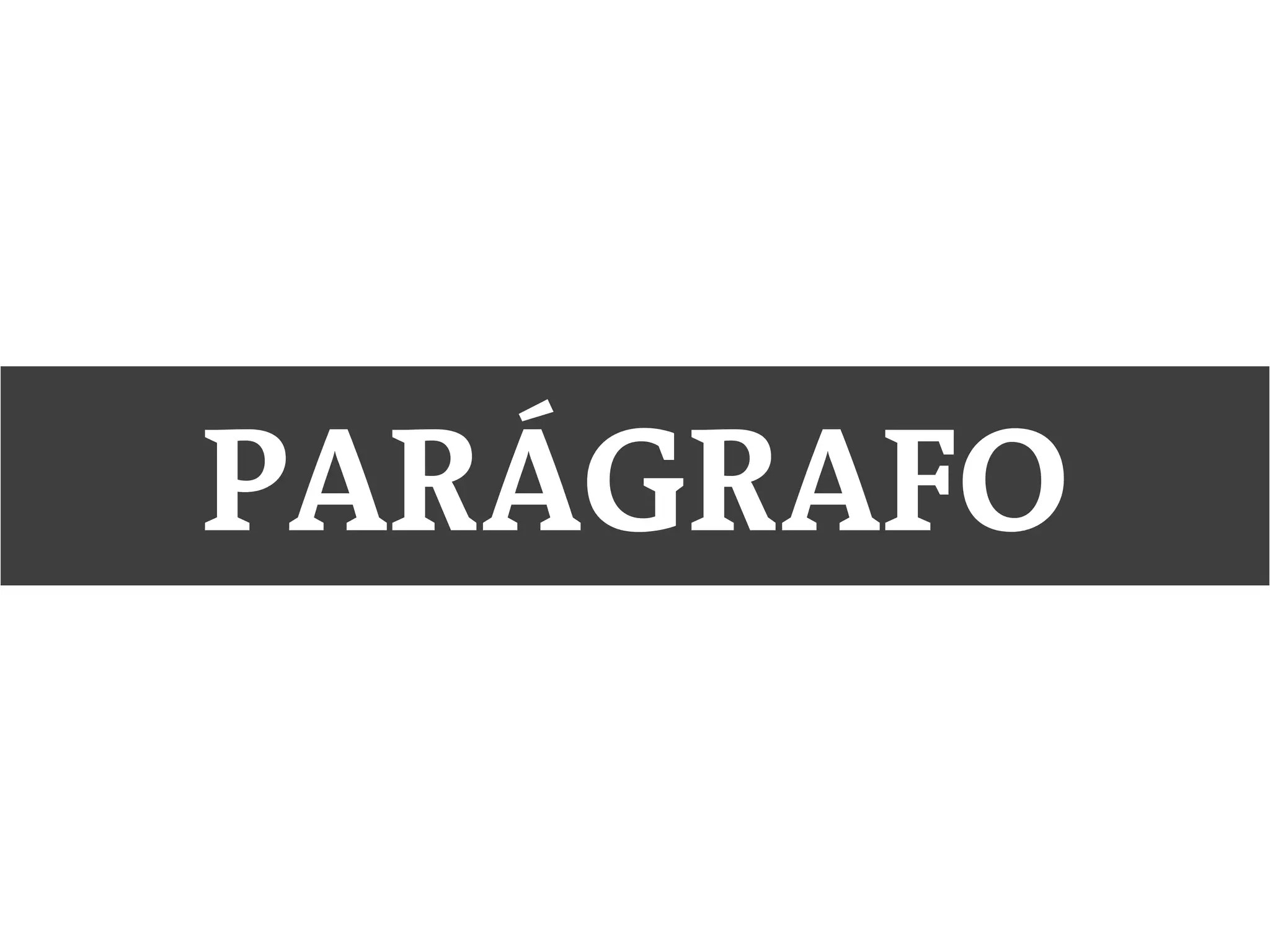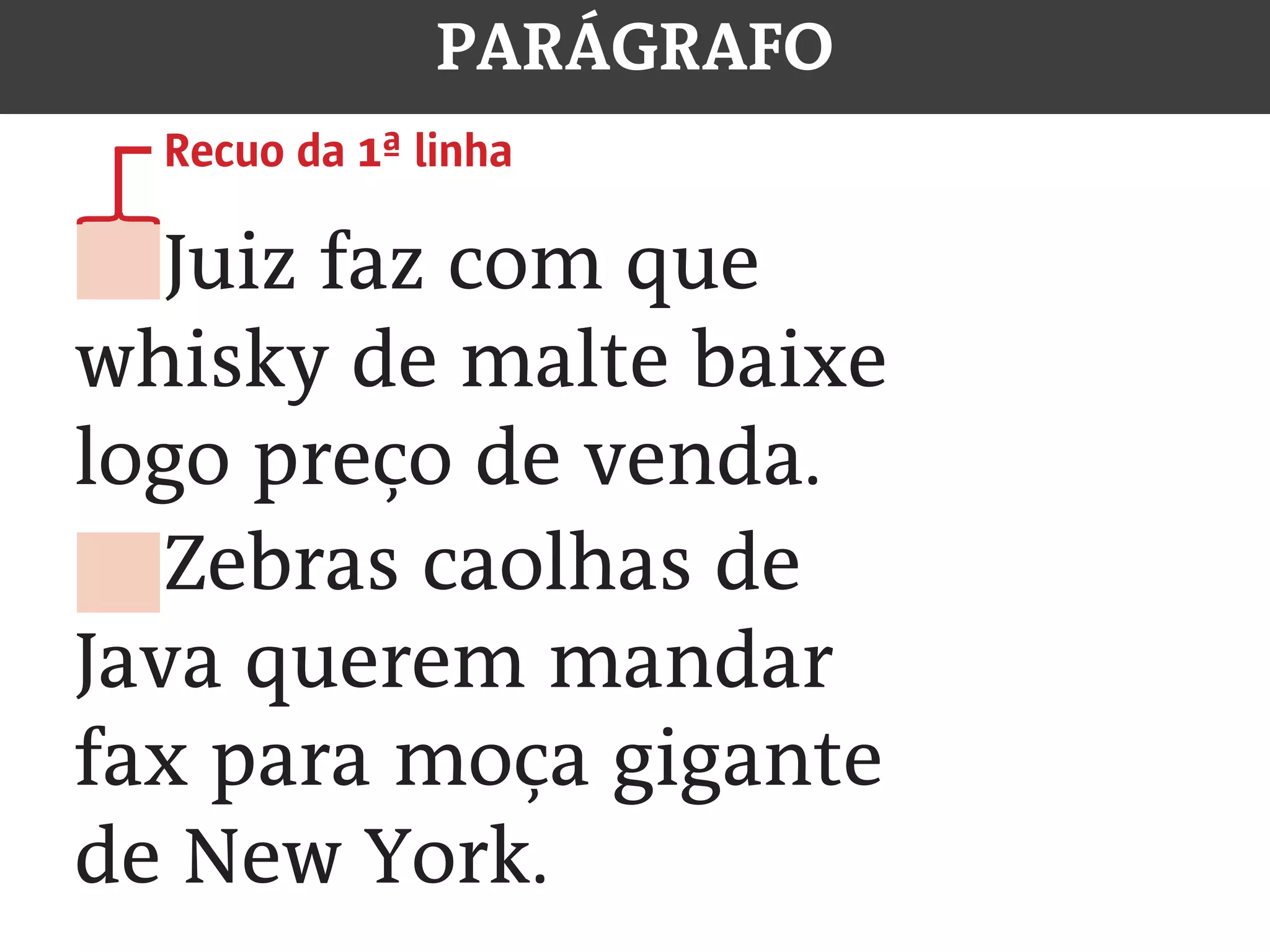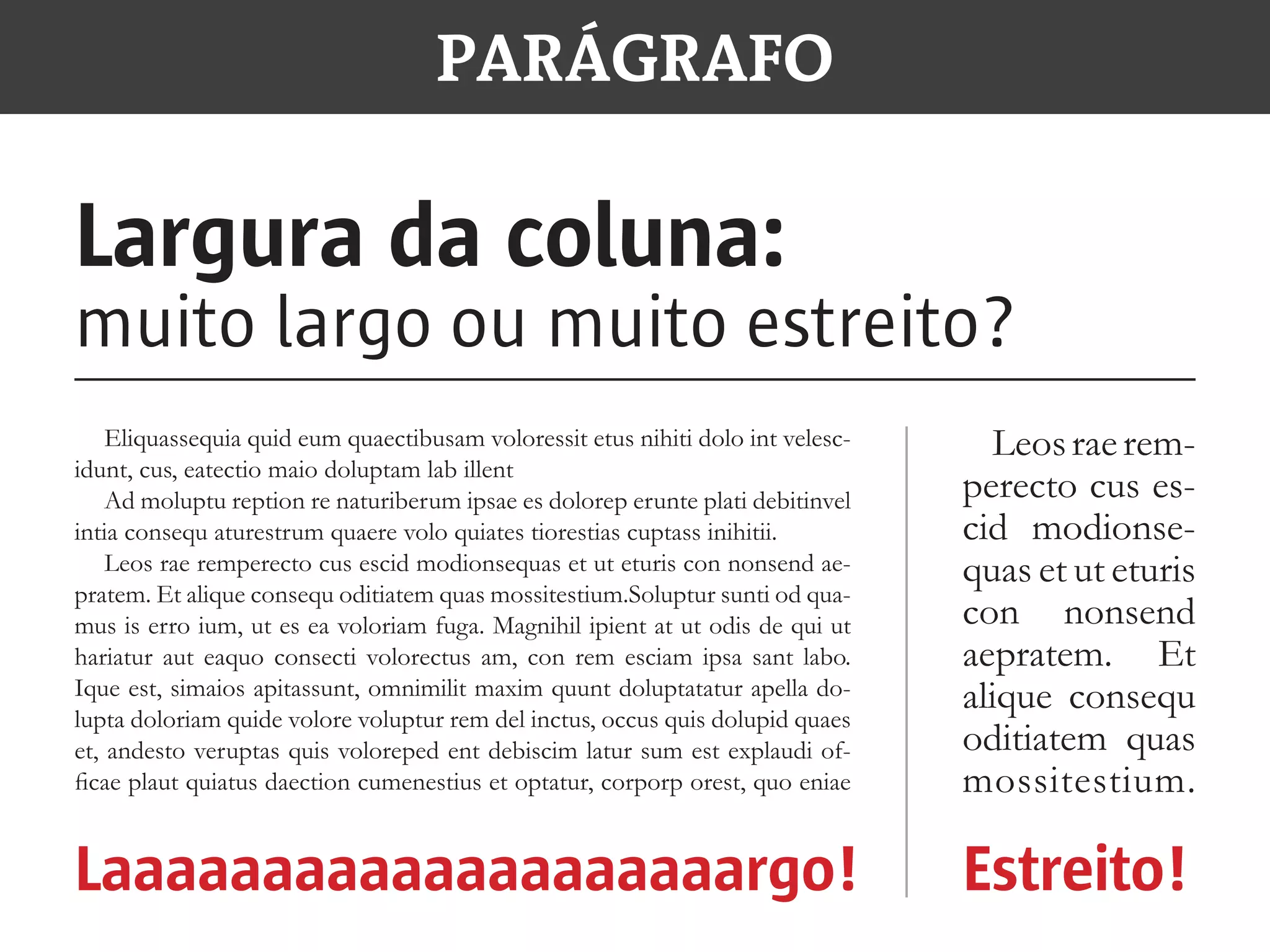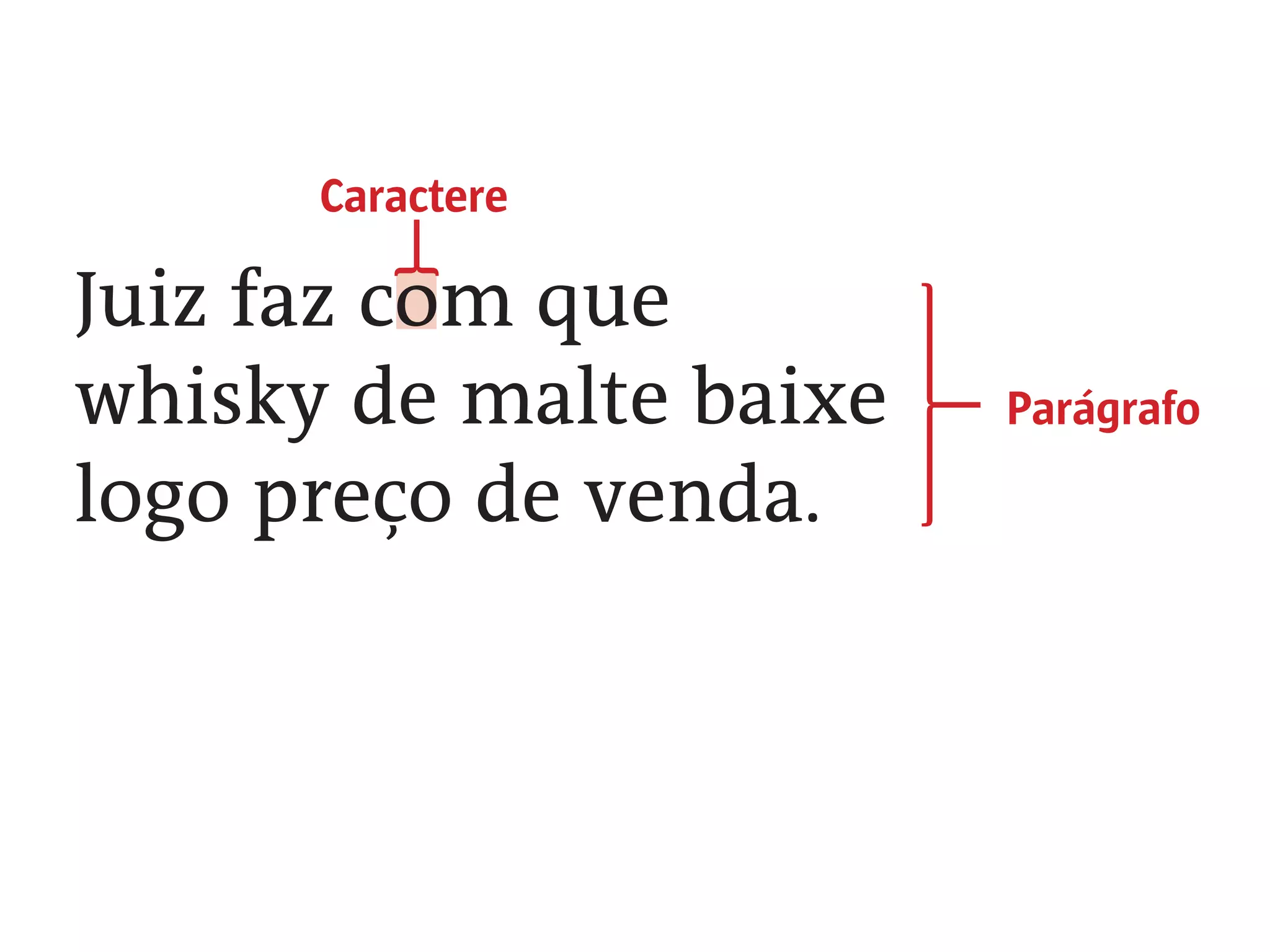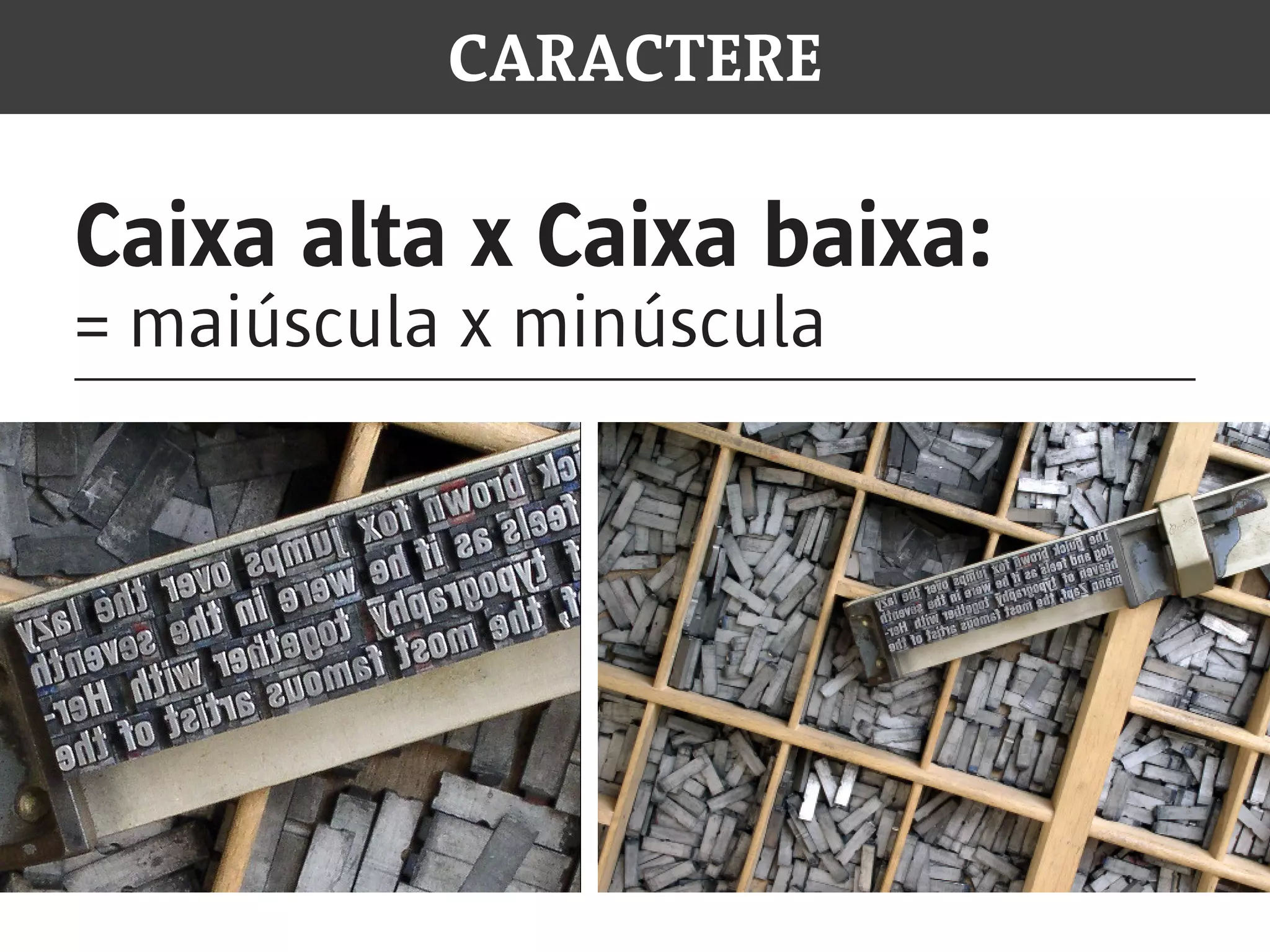
TIPOGRAFIA:
o caractere e o parágrafo
Caractere
{ Parágrafo
CARACTERE
Caixa alta x Caixa baixa:
= maiúscula x minúscula
CAIXA ALTA
caixa baixa
CARACTERE
Caixa alta x Caixa baixa:
= maiúscula x minúscula
CARACTERE
Caixa alta x Caixa baixa:
= maiúscula x minúscula
CARACTERE
Corpo:
é o tamanho do caractere
CARACTERE
Espaçamento (tracking/kerning):
espaço entre os caracteres
CARACTERE
Variações:
modificam o peso e o estilo
Seminegrito(semibold)
Negrito(bold)
Normal(regular)
PESO ESTILO
Itálico
Versalete
Condensado
CARACTERE
Serifas:
ornamentos nas hastes
CARACTERE
Com serifa
Sem serifa
Serifas:
ornamentos nas hastes
CARACTERE
A A
Serifa:
∙ Clássica/Tradicional
∙ Formalidade
∙ Seriedade
∙ Credibilidade
Sans-Serif:
∙ Moderno
∙ Jovem
∙ Dinâmico
Serifas:
ornamentos nas hastes
CARACTERE
Famílias e Fontes:
conjuntos de caracteres de mesmo estilo
Times New Roman Arial
Futura
Garamond
Trajan
Ex. de fontes serifadas Ex. de fontes sans-serif
PARÁGRAFO
Linha
Entrelinha
(entrelinhamento)
Recuo da 1ª linha
Espaço entre
parágrafos
Recuo da 1ª linha
Entrelinhamento (leading):
espaço entre as linhas
Alinhamento:
como o texto serão alinhado?
À esquerda Centralizado À direita Justificado
PARÁGRAFO Largura x entrelinhamento: sãodiretamente relacionadas Após o incidente, o grupo só embarcou para Brasília por volta de 9h30, de acordo com relatos de passa- geiros. Eles reclamaram que a companhia não ofere- ceu nenhum pedido de desculpas e deu poucas infor- mações sobre o problema no avião. “Nós entendemos que o avião não poderia voar na- quelas condições, mas a companhia tem o dever de pedir desculpas e dar mais informações”, afirmou à Após o inciden- te, o grupo só embarcou para Brasília por volta de 9h30, de acor- do com relatos de passageiros. Eles reclamaram